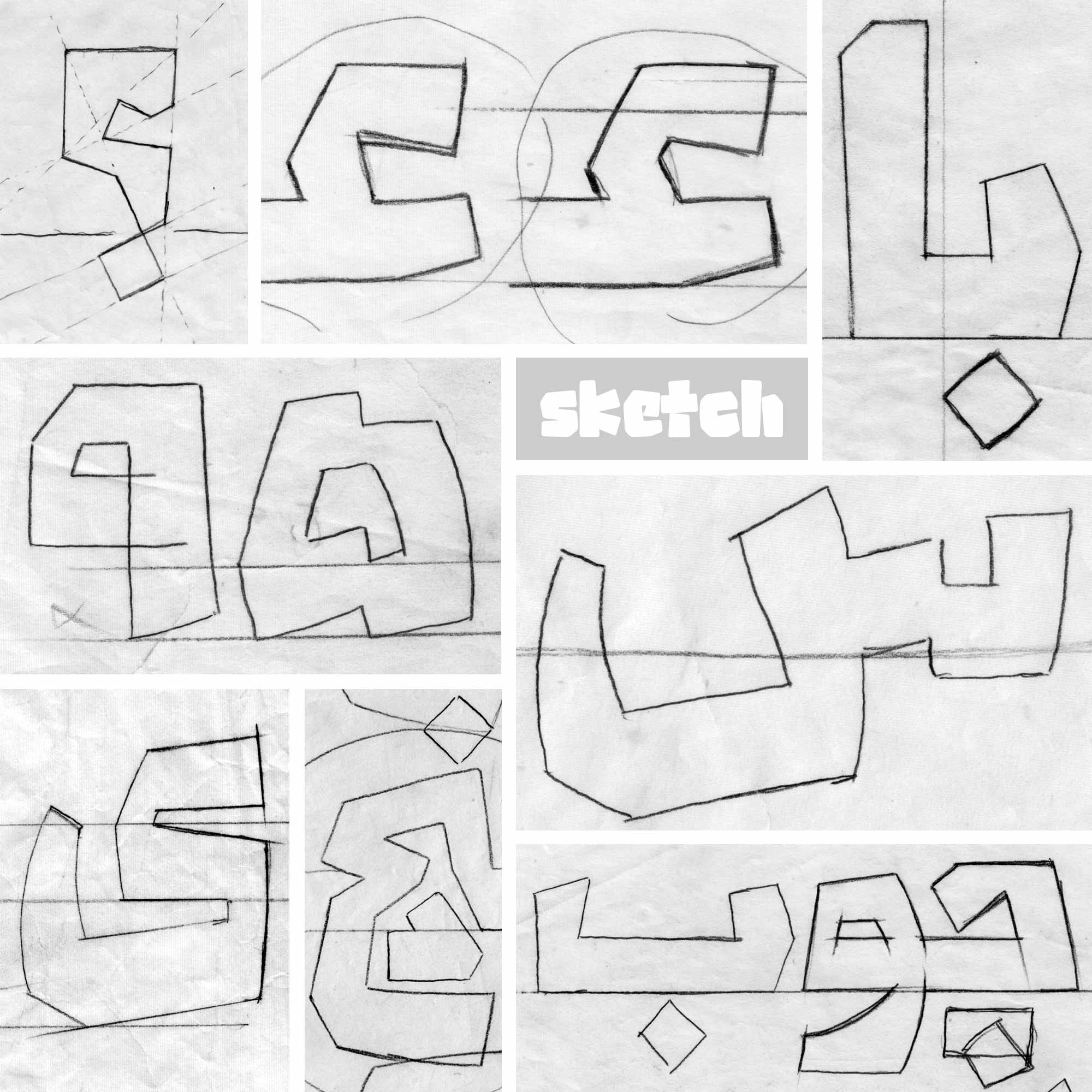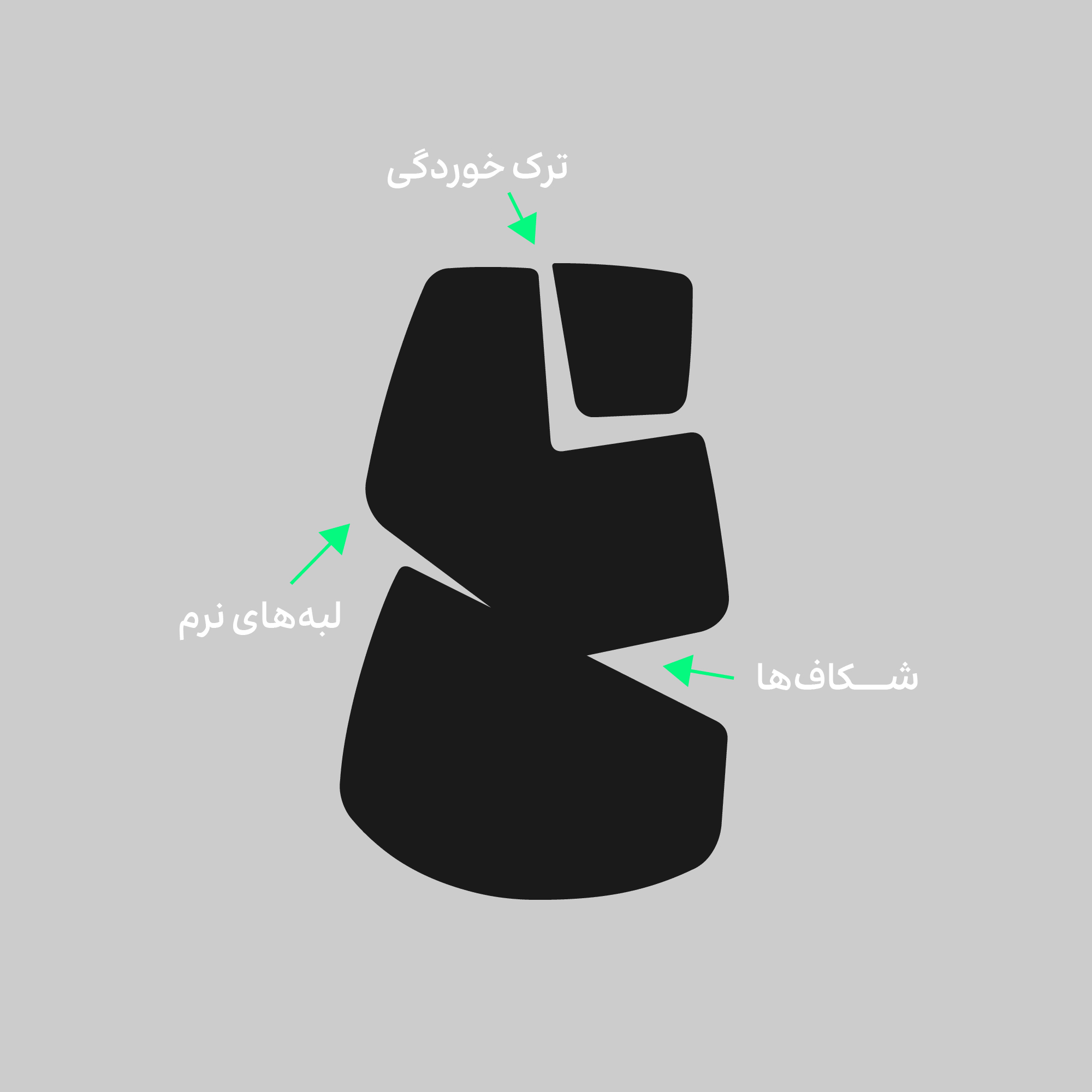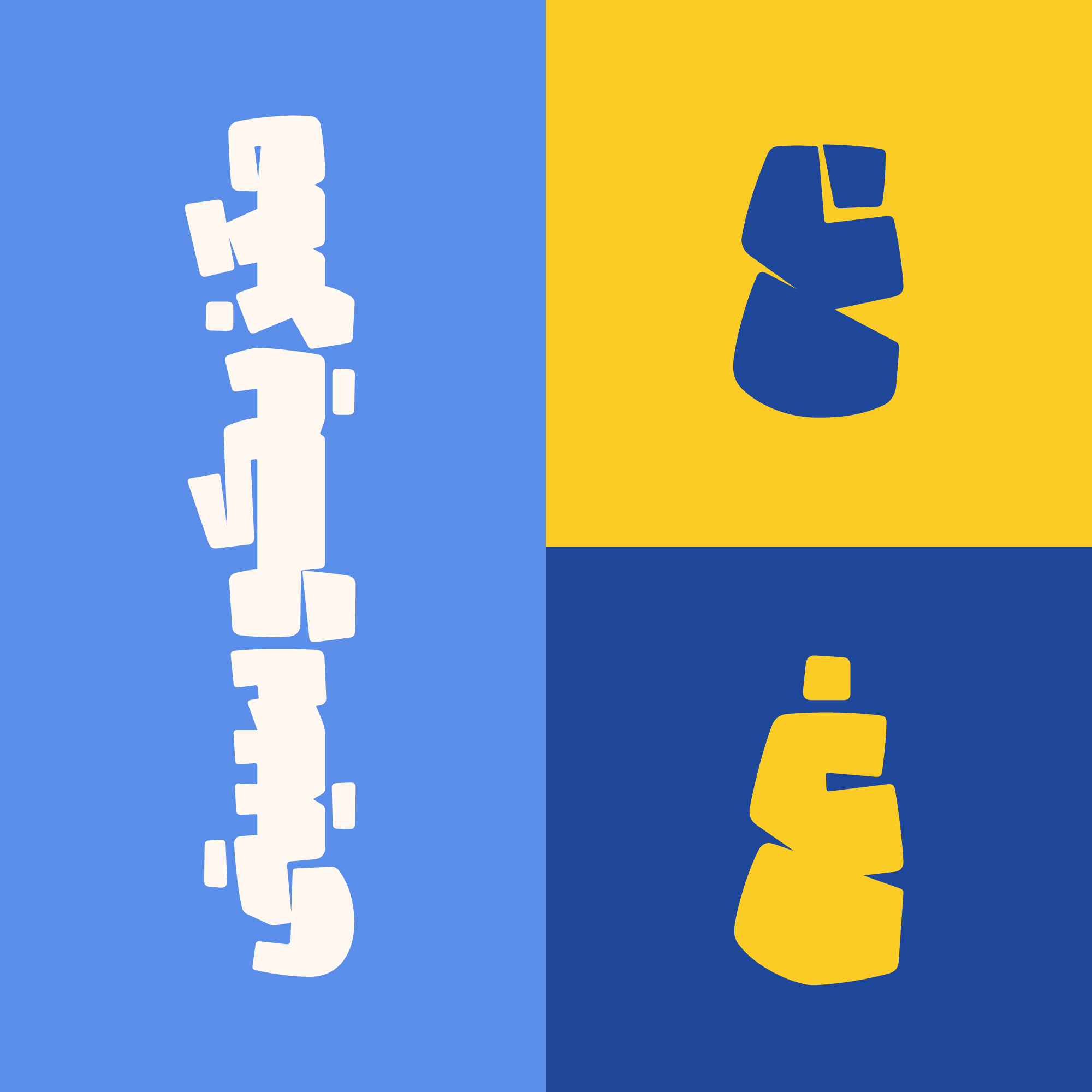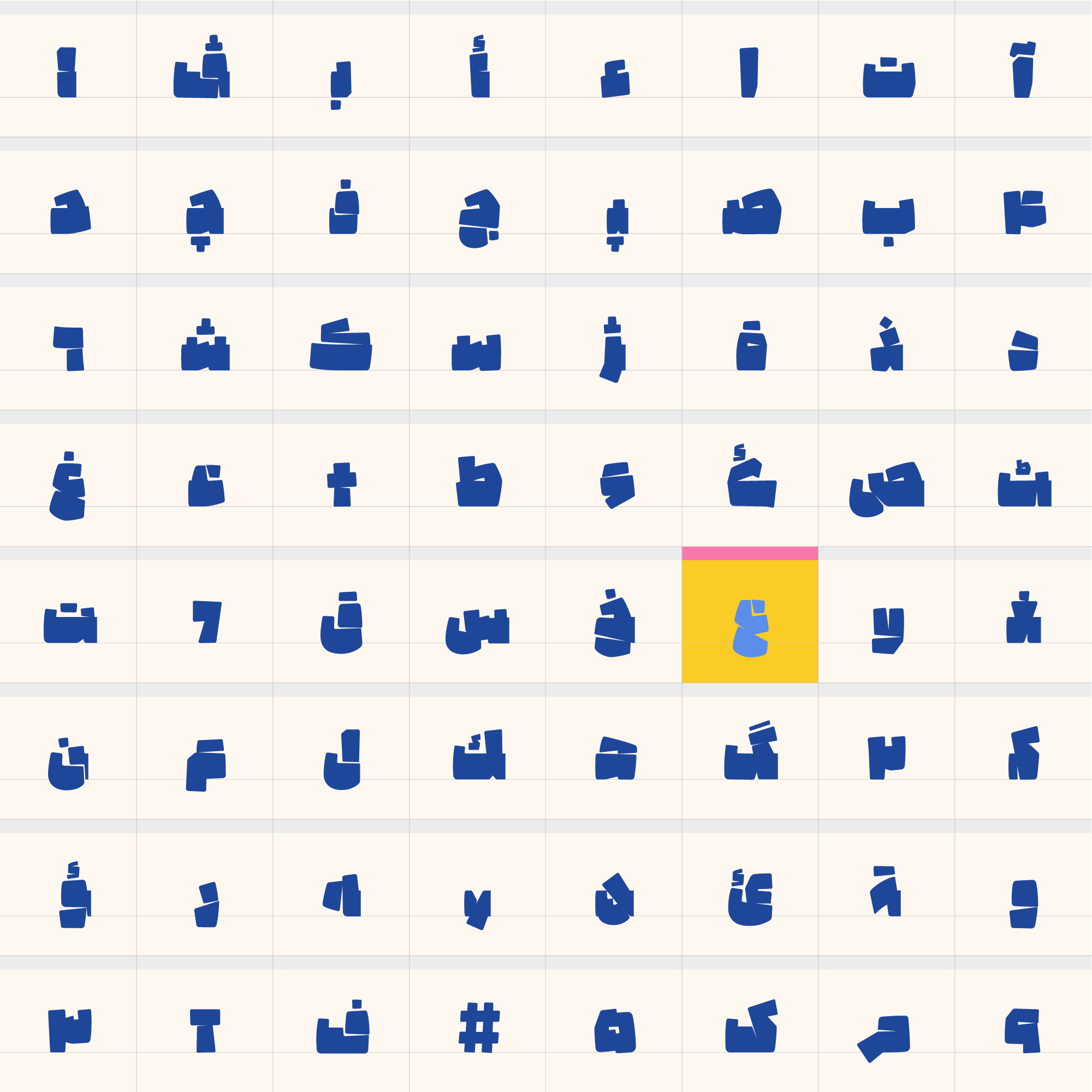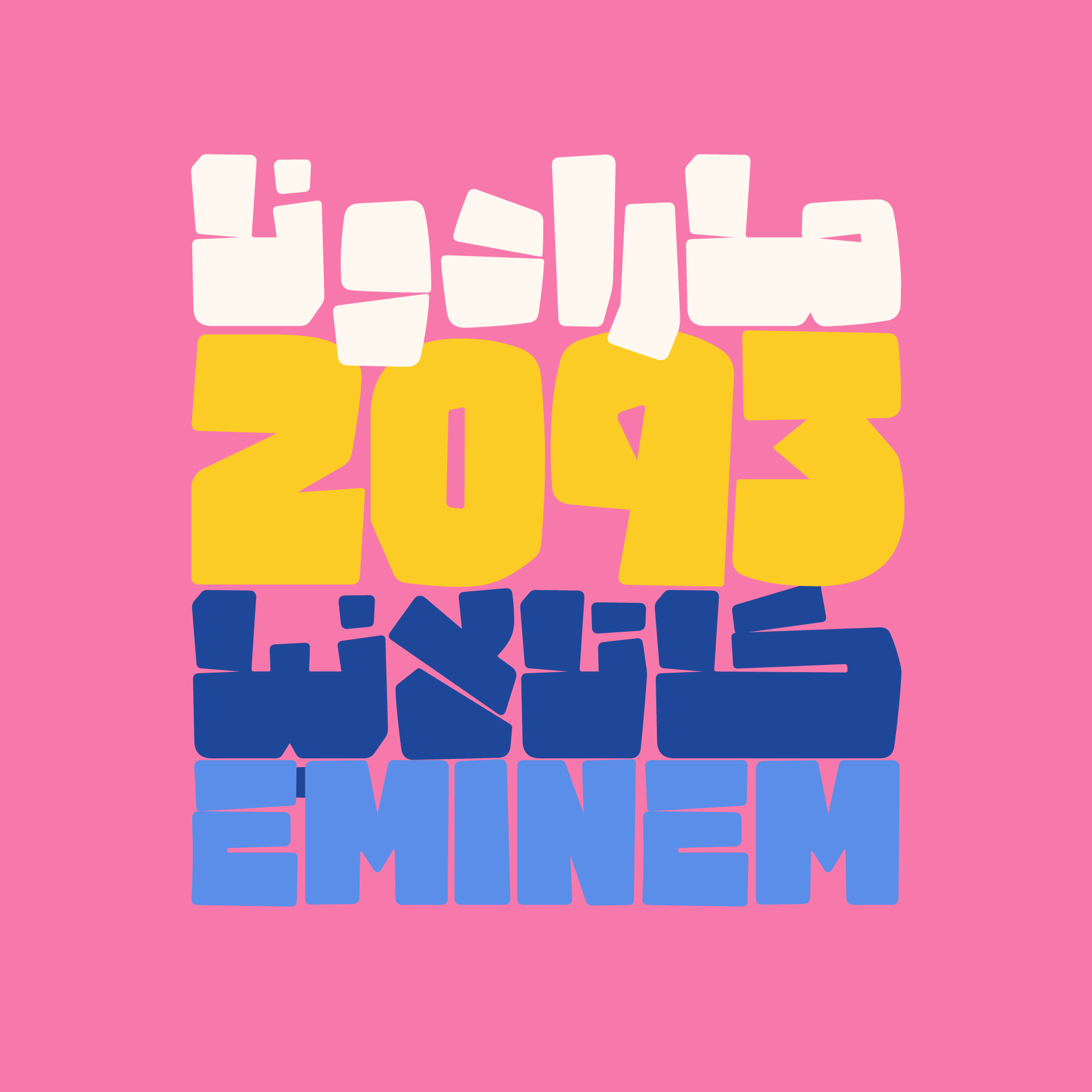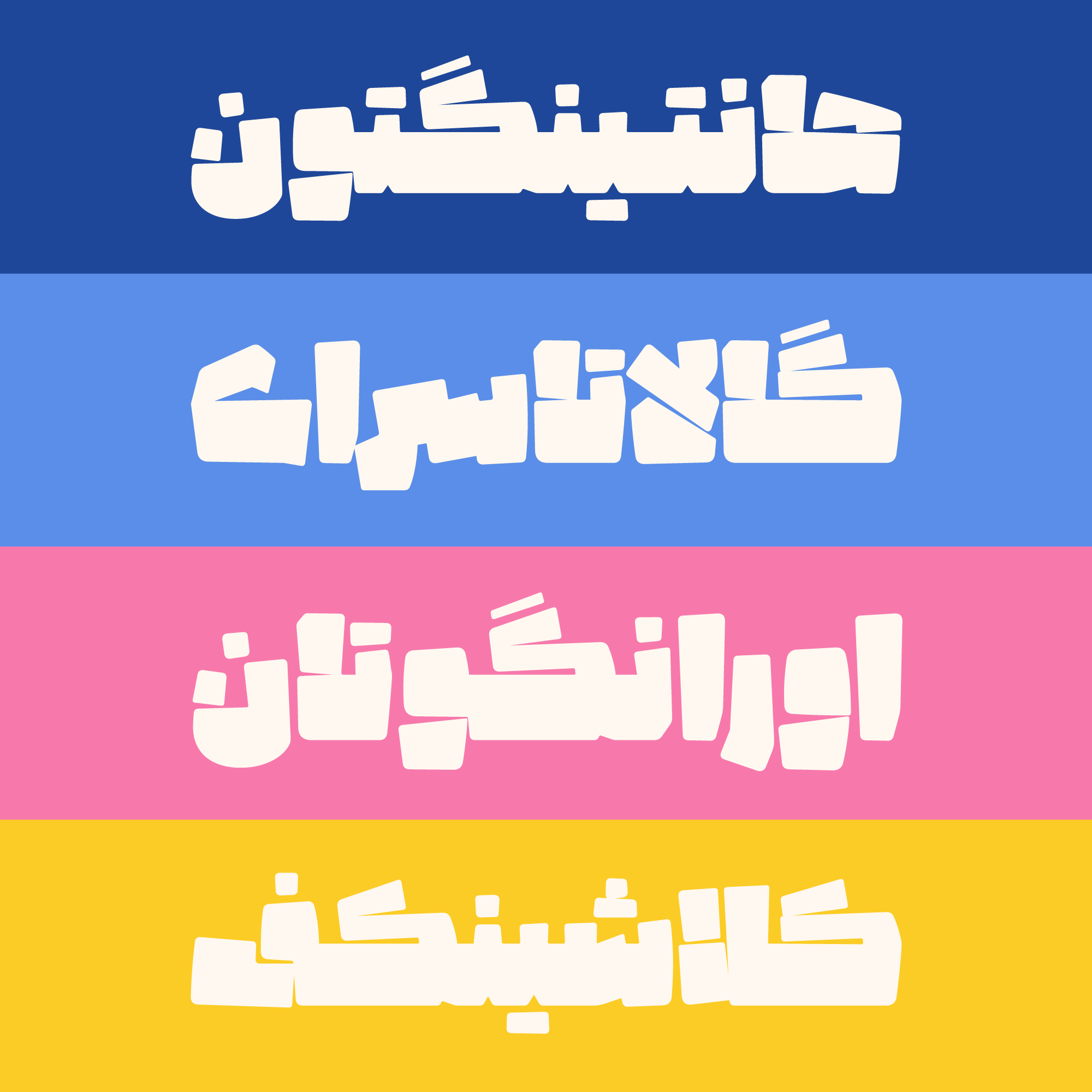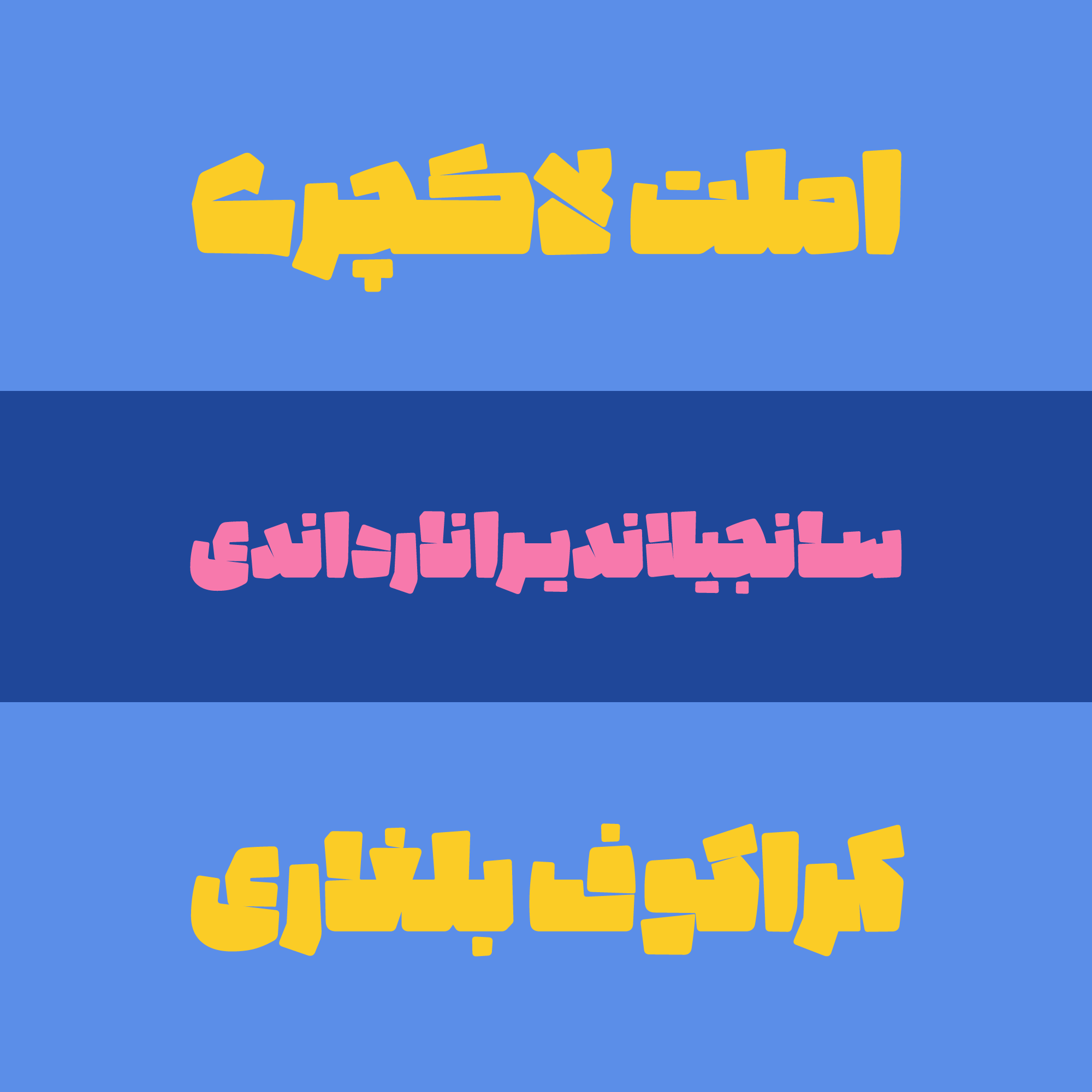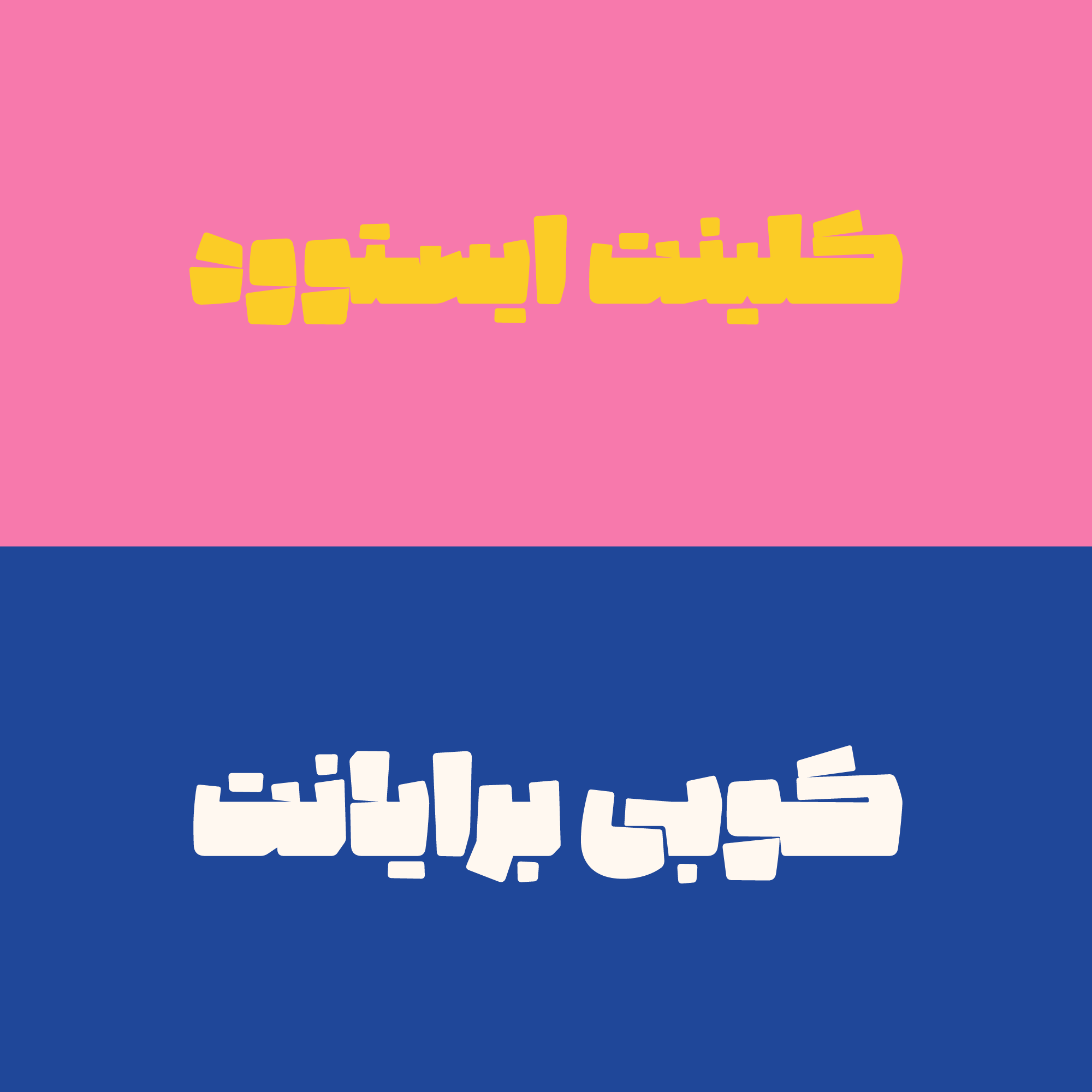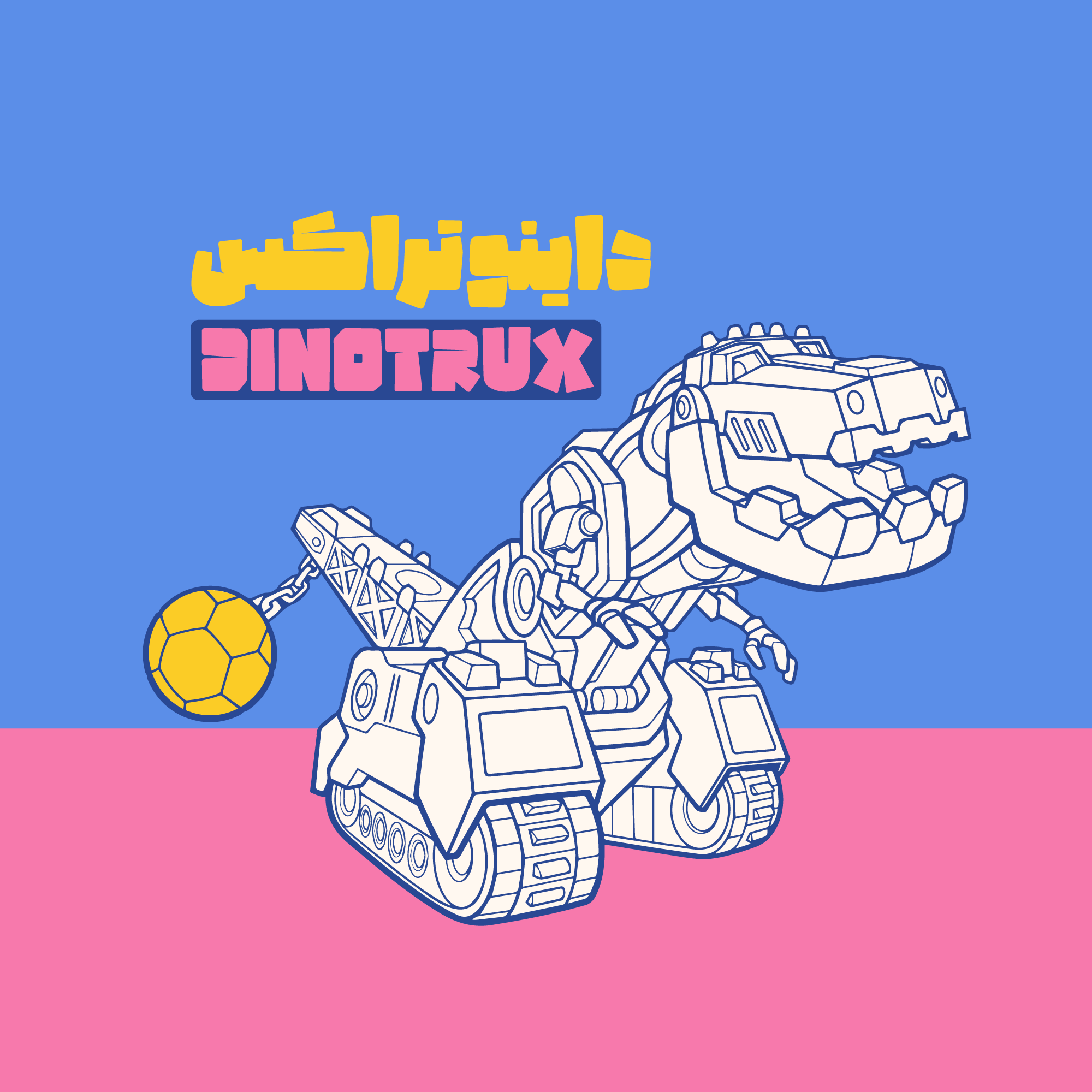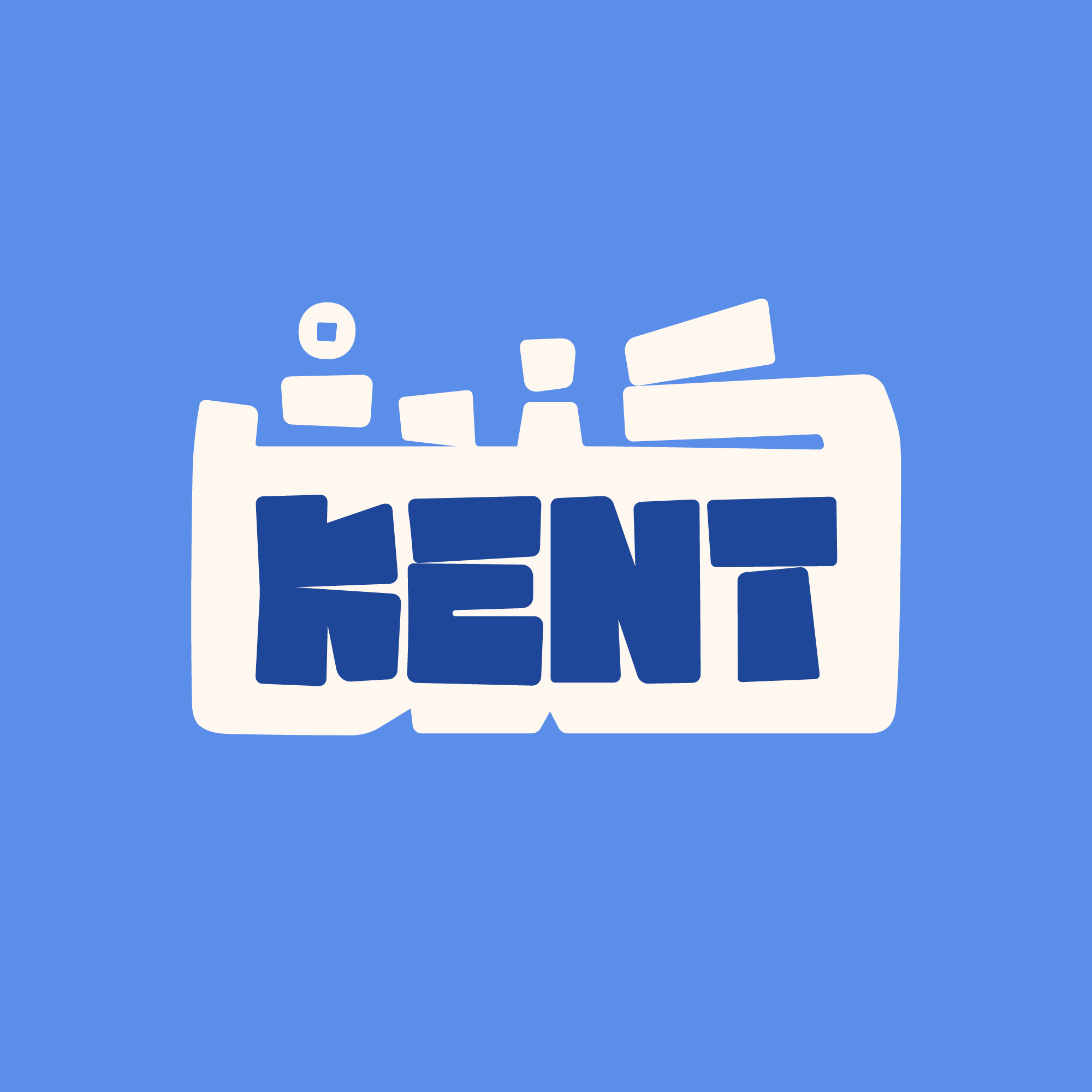
کوبیدن پُتک روی هر چیز به تغییر ریخت اجسام میانجامد و با داشتن ایدهای مناسب میتوان آن را به شکلی خاص بدل کرد.
تفاوتی نمیکند چه چیز زیر ضربات پُتک قرار دارد؛ نحوهی برخورد و شدت ضربهها تعیین کننده است. آهن گداخته، سنگ معادن، بلوکهای سیمانی و حتی حروف قابلیت تغییر شکل دارند.
بیایید تصور کنیم حروف در اثر کوبیدن پُتک بر پیکرهشان چه ریختی پیدا میکنند؟
اگر شدت و قدرت ضربات زیاد باشد چطور؟
چهرهی ظاهری حروف چگونه خواهد بود؟
تغییراتی مثل کم شدن فضای بین حروف و چشمها، برهمزدن یکنواختی در ضخامتها و شکستگیهای اتفاقی و تغییر در اندازهها فضای متفاوتی را در فونت پُتک بوجود آورده است.
فونت پُتک بر اساس همین تغییرات و با پتککاری و بهینهسازی ساخته شده است. لبههای نرم حروف از خوردگیهایِ روی پتک گرفته شده و شکستگیها، بیانگر شکافهایی است که هنگام برخورد ضربات بهوجود میآیند. با کنارهم قرار دادن تکههای کوچک و درشت و همچنین جابجاییهای از پیش تعیین شده شخصیت حروف کامل شده است.
فونت پُتک برای نوشتن عبارات، کلمات و ترکیبهای مختصر کاربرد مناسبتری دارد و برای نوشتن جمله و پاراگراف توصیه نمیشود. یک فونت نمیتواند همهی خواستهها را برآورده کند؛ واقع بینانه بنگرید، لزومی ندارد همهی آنچه میخواهید را در یک فونت جستوجو کنید. با این حال وجود مرکبات، کشیدگیها و ترکیبهای جایگزین میتواند اتفاقات خوبی را رقم بزند.
ضمن در نظر گرفتن اعراب متناسب و متفاوت از نظر جثه تلاش شده تا نقطهها نیز در بسیاری از حروف متمایز باشند تا جلوه نمایشی فونت بیشتر شود.
وجود ترکیب های متنوع در فونت های نمایشی برای خلق عبارت متفاوت امری لازم است. ارائه ترکیب های جایگزین و از پیش تعیین شده برای طراحان کاربردی خواهد بود.
ارائه دو شکل از برخی حروف مثل « ر» «ک» «ه» «ه» برای نمایشیتر کردن یک فونت سودمند است.